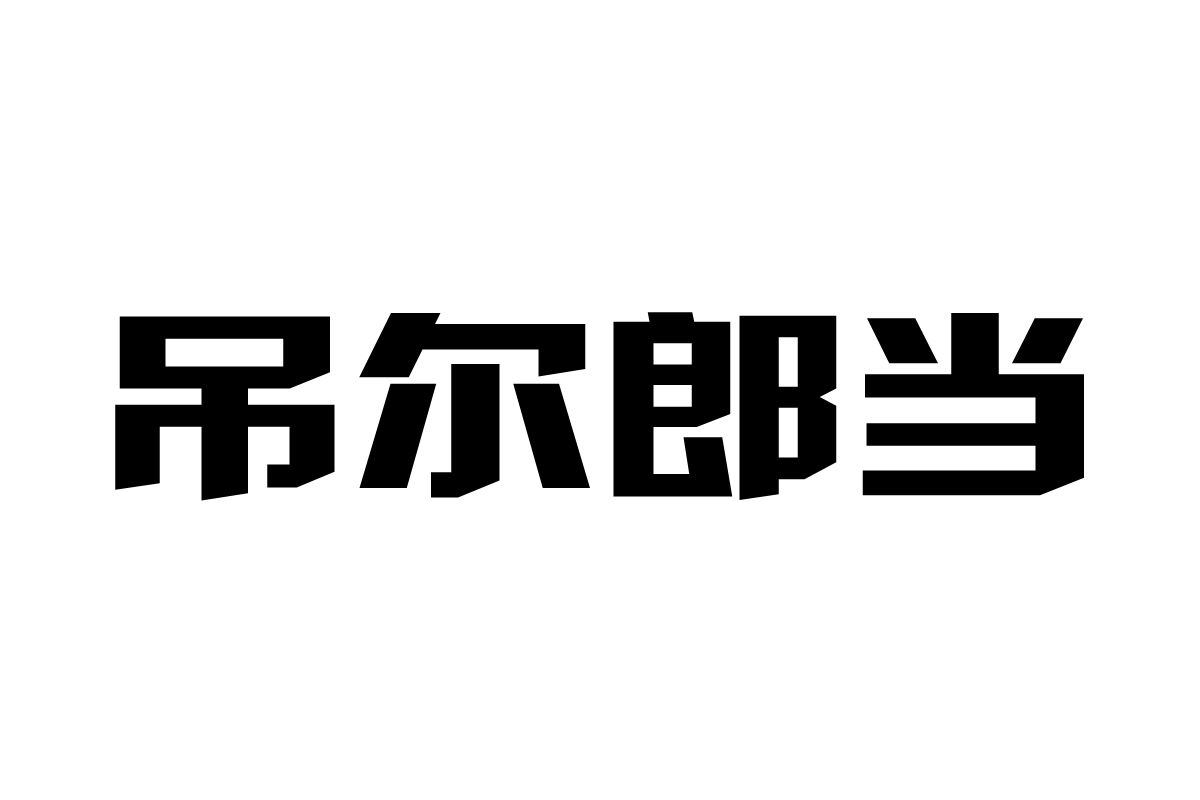
汉仪菱心体摩登版y h3w字体是一款现代感十足的中文字体,由汉仪设计团队精心打造。这款字体具有独特的设计风格,线条流畅、字形规整,适合用于各种商业、广告、设计等领域的文本展示。
汉仪菱心体摩登版y h3w字体的特点如下:
1. 现代感十足:这款字体线条流畅,字形规整,给人一种时尚、前卫的感觉,非常适合用于现代、简约风格的设计。
2. 易于阅读:字体笔画粗细适中,间距均匀,使得文字在视觉上更加清晰、易读,提高了文本的整体可读性。
3. 适用范围广泛:汉仪菱心体摩登版y h3w字体适用于各种商业、广告、设计等领域的文本展示,如海报、宣传册、网页等。
总之,汉仪菱心体摩登版y h3w字体是一款功能强大、风格独特的中文字体,适用于各种商业、广告、设计等领域的文本展示。